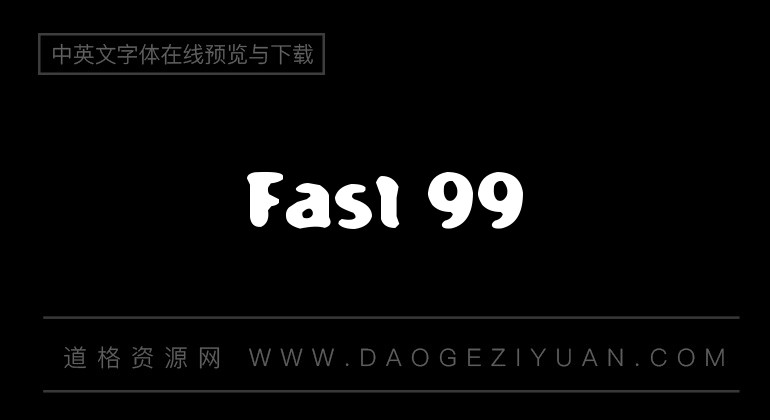
Fast 99 字体是一款由德国设计师 Christian Thalmann 创作的线条简约字体,它采用现代设计理念,融合了传统字体的美学,让字体在极简主义的现代设计中更加凸显出来。Fast 99 字体以线条简洁的设计风格,搭配出色的可读性,以及轻松的设计感,为各类设计项目提供了一种简洁的现代风格。内容介绍
Fast 99是一款非常不错的手写艺术字体,具有很好的视觉感,适合于文化类的宣传设计、商业类品牌的广告和产品包装设计以及个性化文字排版等较多场景。